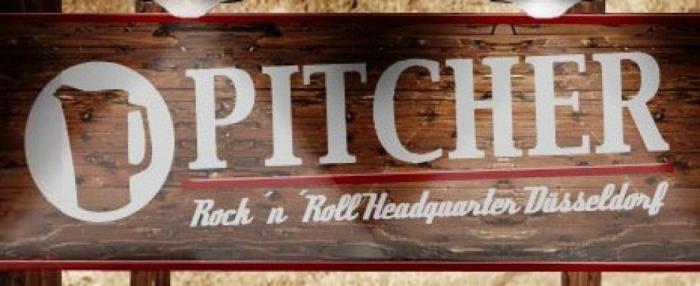
kann mir jemand behilflich sein diese Schriften zu finden?
Bei Identififont, What Font is und What the Font habe ich leider nicht das Richtige gefunden
Die beiden Striche, die wohl Apostrophe sein solle, finde ich bemerkenswert …  :twisted:
Die Deftone hatte ich auch schon im Auge, war mir aber nicht ganz sicher. Liegt wohl an der schlechten Auflösung vom Bild